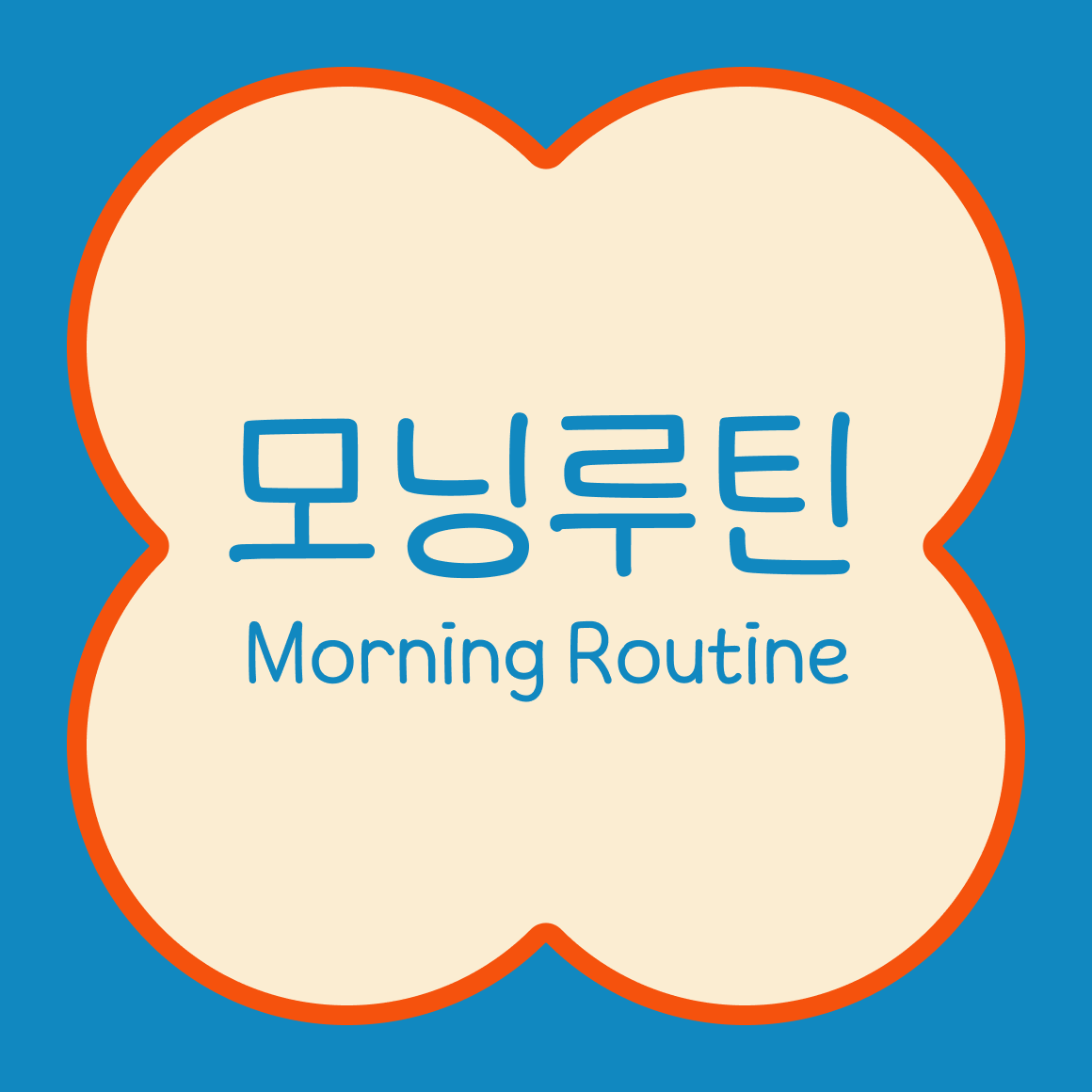
SD 모닝루틴
SD 모닝루틴은 안정감 있는 꽉 찬 네모꼴에 쭉쭉 시원하게 뻗은 자소가 어우러져, 힘차게 하루를 시작하는 에너지를 담은 손글씨 폰트입니다. 한 획 한 획 또박또박 눌러쓴 듯한 필감과 안정감 있는 글줄이 특징으로, 긴 문장과 작은 크기에서도 편안한 가독성을 보여줍니다. 브이로그 영상 자막, 다이어리 등 일상을 기록하는 다양한 콘텐츠에 활용하기 좋습니다.